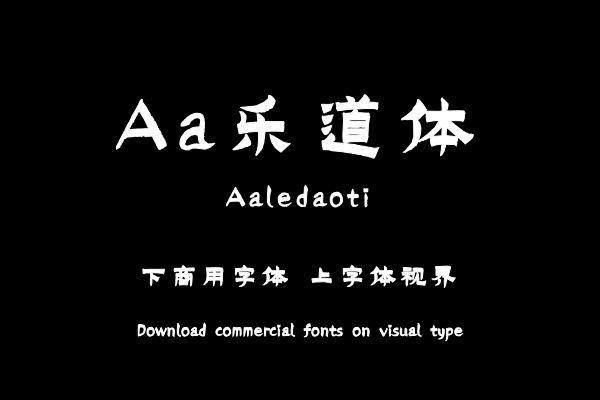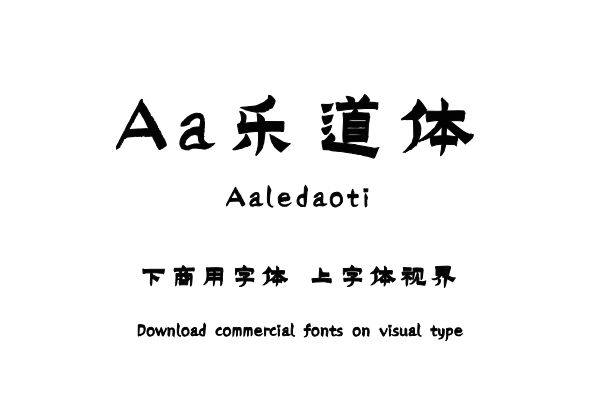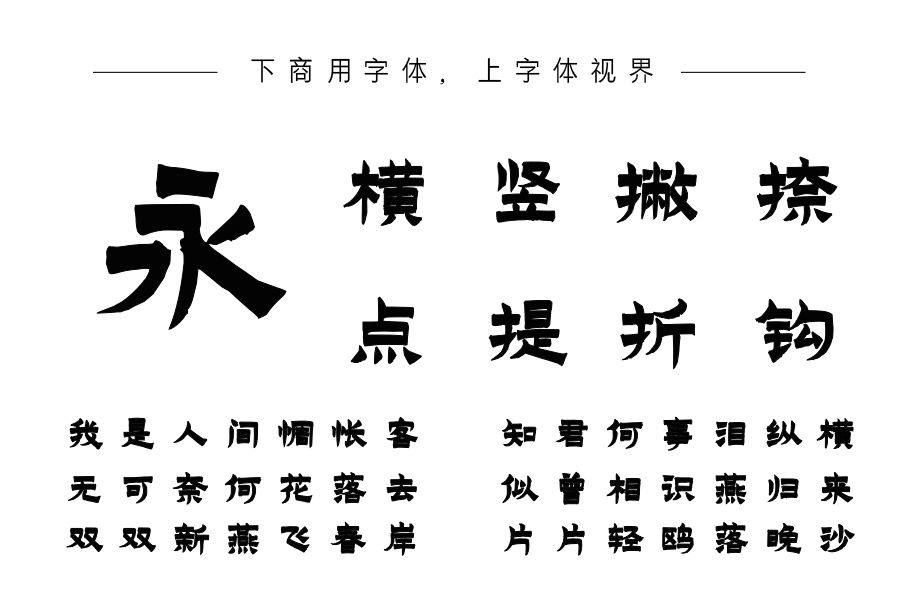
本字体承袭金农漆书扁平的刷子蘸上浓墨写就的横画,有横粗竖细的逆反差效果,尖锐的钩和撇等笔画打破横画的粗重稳定,加强了动态,增添了装饰性,传达了古朴清新的视觉感受......购买须知:“下载服务费”与“字体VIP”所获得字体 仅用于个人非商用, 商用请联系付费授权。本字体为电脑用字,手机没有root权限不支持直接手机换字(手机如何root,请自行百度搜索教程)。购买前请先 了解清楚后再付款 ,字体为虚拟产品无法回收 一旦购买不支持退款。